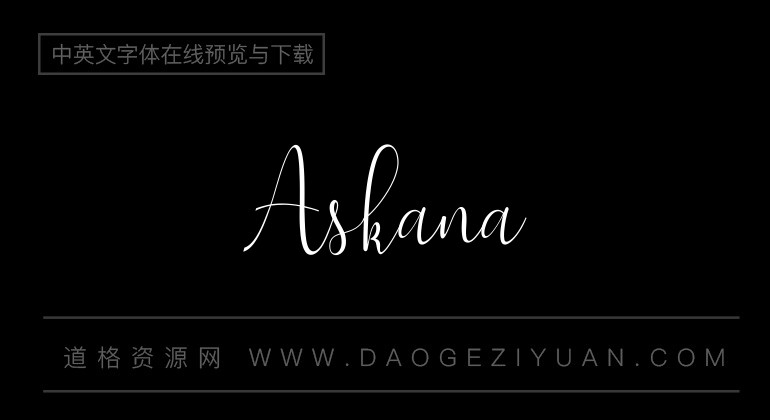
Askana
Askana 是一款由字体设计师 Alex Slobzheninov 于 2019 年开发的英文字体,它是一款极具特色的新字体,具有宽松、自由、活泼的风格。它的字符设计具有独特的节奏感,能够营造出一种活力十足的氛围。它的字形结构比较简单,以及其明快的线条,能够使得文字更加有趣和活泼。此外,它还具有卓越的可读性,能够让文字更加清晰。Askana 字体适合用于平面设计、网页设计、印刷出版物以及各种宣传材料等多种应用场景。
Askana是一款非常不错的手写艺术字体,具有很好的视觉感,适合于文化类的宣传设计、商业类品牌的广告和产品包装设计以及个性化文字排版等较多场景。
Askana字符映射图